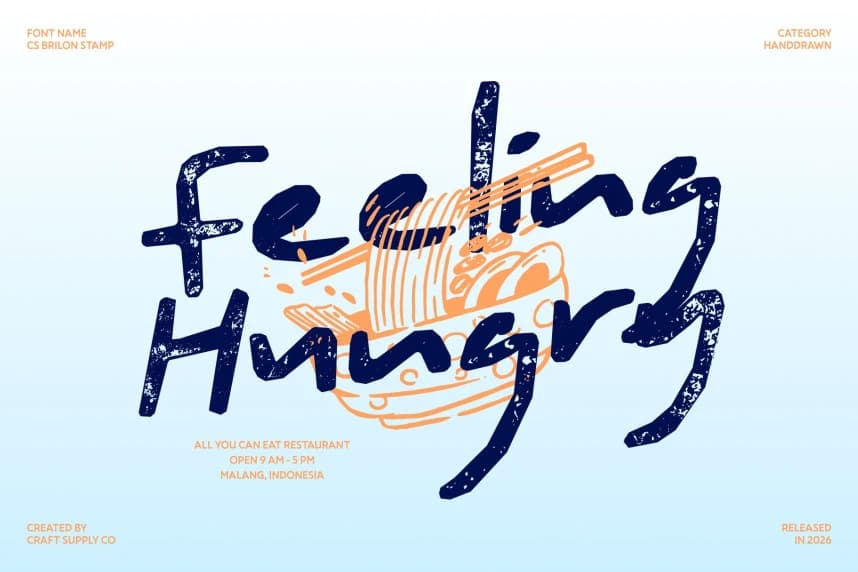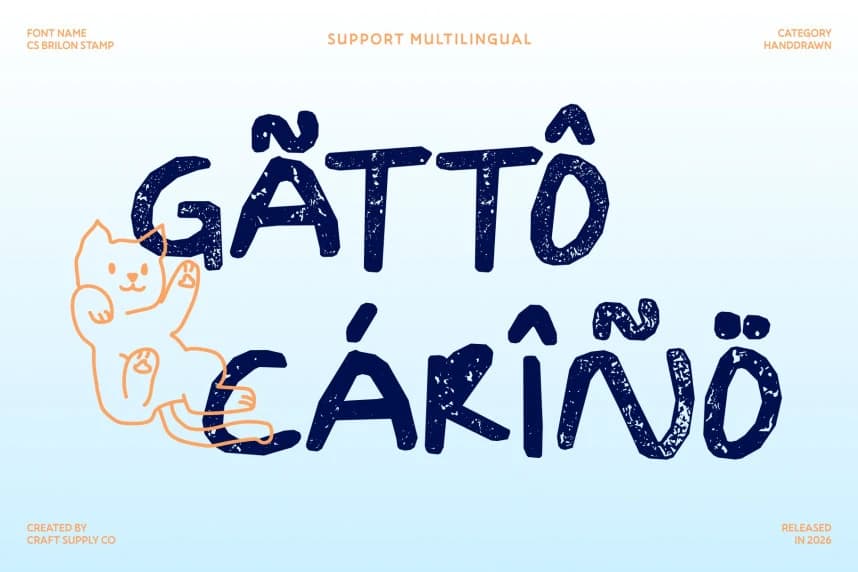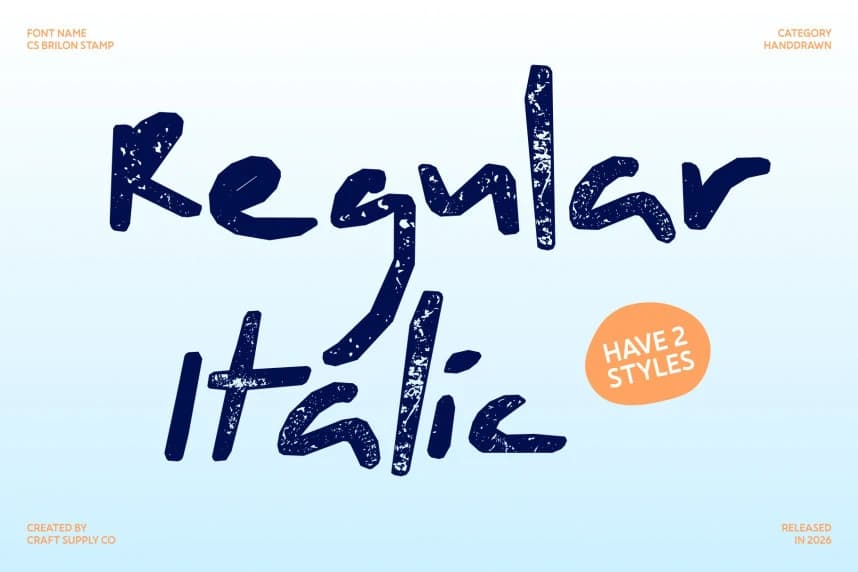
CS Brilon Stamp Font
CS Brilon Stamp Font – Dokuya sahip organik el çizimi ifade ile ham karakterli el çizimi görünümüne sahip sans serif görüntü yazı tipidir. Bu, sanatsal özgürlüğü ve organik ifadeyi kutlamak amacıyla yaratılmıştır.
CS Brilon Stamp Font – Organik El-Çizimli İfade ile Dokulu Ruh; Ham Karakterli El-Çizimli Gösterim Yazı Tipi. Bu, sanatsal özgürlüğü ve organik ifadeyi kutlamak için tasarlanmış bir el-çizimi sans-serif yazı tipidir.